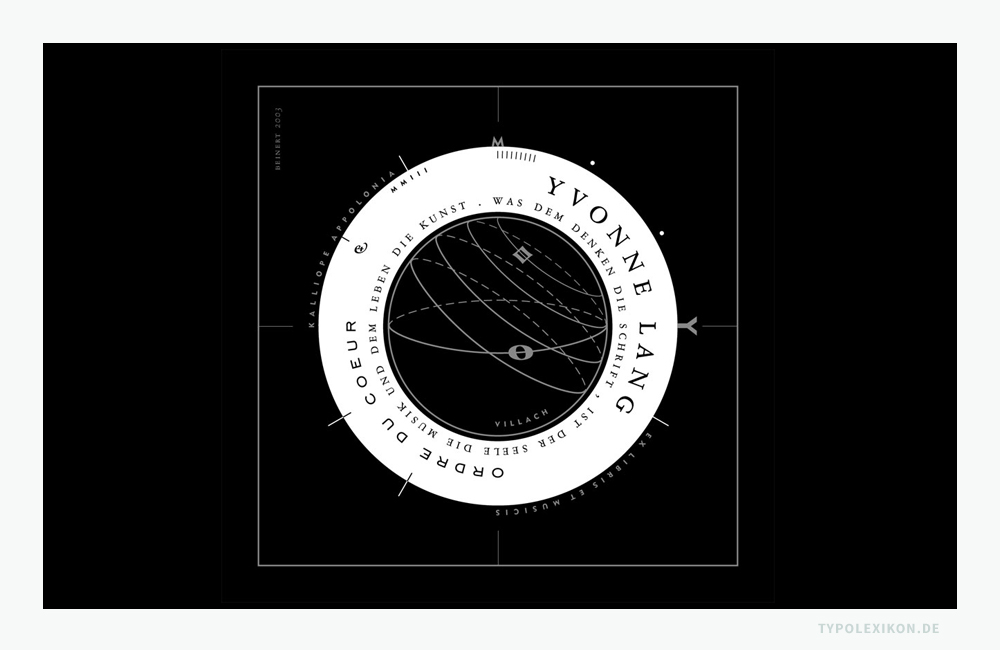
Exlibris
Buchbesitzzeichen; Bücher- oder Bibliothekszeichen; typografisches oder/und grafisches Bucheignerzeichen oder -geberzeichen. In ein Buch geklebtes, drucktechnisch vervielfältigtes, kleinformatiges (Papier-)Blättchen, das auf den Besitzer des Buches hinweisen soll. Alternative Schreibweise »Ex Libris«.
Da Buchbesitzzeichen ursprünglich von Besitzern ganzer Bibliotheken verwendet wurden, bürgerte sich auf ihnen die Inschrift »Ex libris« vor dem Namen des Eigentümers ein, weshalb sie auch kurz »Exlibris« genannt wurden. 1)  Hypostasierung des Substantivs »Exlibris« (Pluralitantum) von lat. »ex libris« für »aus den Büchern« bzw. übertragen »aus der Bibliothek« oder »aus der Bücherei«. 2)
Das Exlibris entwickelte sich in Deutschland in der ersten Hälfte des 15. Jahrhunderts mit dem Wiege- bzw. Inkunabeldruck aus der Tradition kalligraphischer und illuminierter Besitzervermerke, Deckelpressungen (z.B. Supralibros) und Gravuren auf den Metallschließen des Bucheinbandes. 3) Experten gehen davon aus, dass die ältesten Exlibris (z.B. Igler-Exlibris, Buxheimer Exlibris) zwischen 1470 und 1491 im Holzschnitt entstanden sind. Exlibris wurden anfänglich vom Adel, der Geistlichkeit und von reichen Patriziern bei Offizinen in Auftrag gegeben. Neben seiner ursprünglichen Verwendung als Eigner- oder Geberzeichen wird das Exlibris heute insbesondere als Sammlerobjekt verwendet. Ein Exlibris wird traditionell auf den inneren Vordeckel (linker vorderer Vorsatz) eines Buches eingeklebt. 4)
Exlibris der Münchner Hofbibliothek aus dem Jahre 1618. Quelle: Bayerische Staatsbibliothek, München.
Typografisches Exlibris einer Musikwissenschaftlerin und Germanistin aus dem Jahre 2003. Dieses quadratische Buchbesitzeichen enthält vielerlei Andeutungen, die sich auf den Lebensweg der Eignerin beziehen. Grafikdesign: © Wolfgang Beinert, Berlin.
Typografisches Exlibris einer Musikwissenschaftlerin und Germanistin aus dem Jahre 2003. Dieses quadratische Buchbesitzeichen enthält vielerlei Andeutungen, die sich auf den Lebensweg der Eignerin beziehen. Grafikdesign: © Wolfgang Beinert, Berlin. Weiterführende Informationen online verfügbar unter https://www.wolfgang-beinert.de/portfolio/grafikdesign-webdesign-yvonne-lang-austria/.
Im Exlibris vereinen sich buchwissenschaftliche, gestalterische und soziologische Aspekte. Ein schlichtes typografisches Exlibris (Schriftexlibris) besteht aus dem auf einem Blatt gedruckten Hinweis »Ex libris« sowie dem Namen des Eigentümers oder des Schenkers bzw. Stifters (z.B.: »Ex libris Wolfgang Beinert« für »Aus der Bibliothek von Wolfgang Beinert«). Alternative Formulierungen können u.a. »Dieses Buch gehört …« oder »Signum bibliohecac …« sein. Darüber hinaus kann ein grafisches Exlibris Worte, Wahl- oder Sinnsprüche, Illustrationen, Fotos, Monogramme, Wappen, Emblemata, Symbole, Signete etc. enthalten, die auf die Vorlieben, den sozialen Status oder die Biographie des Besitzers hinweisen. Oft beinhaltet die Gestaltung eines Exlibris auch versteckte Anspielungen, Codes oder verschlüsselte Botschaften, die sich dem Betrachter auf Anhieb nicht erschließen.
Exlibris werden infolge der Exlibriskunst und des Sammelns in unterschiedliche Kategorien und charakteristische Gruppen eingeteilt, beispielsweise in
• Bucheignerexlibris (Eigentümer des Buches)
• Donatorenexlibris (Stifterexlibris, Buchgeberexlibris)
• Doppelexlibris (z.B. Wappen- und Inschriftblättchen oder zwei Eignerexlibris zweier Besitzer einer Bibliothek, z.B. Eheleute)
• Eigenexlibris (das Exlibris eines Designers bzw. bildenden Künstlers, das er für sich selbst gestaltet hat)
• Einklebeexlibris
• Gebrauchsexlibris (Exlibris, das nicht auf das Sammeln ausgerichtet ist)
• Luxusexlibris (Exlibris, das bereits bei der Gestaltung auf einen hohen Sammlerwert ausgelegt ist)
• Stempelexlibris (Buchstempel)
• Supralibros (geprägtes Super-Exlibris)
• Universalexlibris (loses Blatt oder bereits im Buchdeckel eingedruckt, so das der jeweilige Besitzer seinen Namen selbst eintragen kann)
• Ornament-, Schrift- und Textexlibris. 5)
Exlibris werden in der Regel von Typografen/innen, Grafikdesignern/innen (siehe Grafikdesign), Illustratoren/innen oder bildenden Künstlern/innen gestaltet und in unterschiedlichen Drucktechniken, z.B. in Hochdruckverfahren, Tiefdruckverfahren oder photomechanischen Verfahren [6] hergestellt. Bedruckt werden mehrheitlich industriell hergestellte oder handgemachte grafische Papiere 6)  in unterschiedlichen Sorten. Gebrauchsexlibris erreichen selten Formate über dem traditionellen Oktavformat, welches etwas kleiner als ein Taschenbuch ist. Luxusexlibris sowie Eigenexlibris können auch größere, unzweckmäßige Formate aufweisen.
Im Sinne der Kunstgeschichte gelten das 16. Jahrhundert und die Epoche des Jugendstils (Jahrhundertwende, etwa 1896–1910) als die Blütezeiten der Exlibriskunst. Zu den prominenten Gestaltern von Exilbris zählen beispielsweise Albrecht Dürer (1471–1528), Hans Holbein der Jüngere (1497/98–1543), Lucas Cranach der Ältere (1472–1553), 7)  Giambattista Bodoni (1740–1813), Wilhelm Busch (1832–1908), Pablo Picasso (1881–1973) oder Jan Tschichold (1902–1974). Große öffentliche Exlibrissammlungen besitzen u.a. das British Museum in London, die Bayerische Staatsbibliothek in München, die Österreichische Nationalbibliothek in Wien, das Gutenberg-Museum in Mainz und das Germanische Nationalmuseum in Nürnberg (siehe Museen Typografie und Schrift). Die Zahl der Privatsammlungen ist unbestimmbar. Zahlreiche Sammler haben sich weltweit in sogenannten Exlibrisgesellschaften und -vereinen organisiert. In Deutschland wurde 1891 der erste Verein dieser Art von Friedrich Warnecke (1837–1894), einem deutschen Heraldiker und Kunsthistoriker, unter dem Namen »Ex-libris-Verein zu Berlin« gegründet. 8)  9)  10)  11)
↑1 Quelle: Meyers Konversations-Lexikon (5. Auflage) von 1897, Verlag des Bibliographischen Instituts, Leipzig und Wien.
↑2 Quelle: Kluge, Etymologisches Wörterbuch der deutschen Sprache, 24. Auflage, Walter de Gruyter, Berlin/New York.
↑3 Quelle: Gustav A. Seyler, Kanzleirath, Bibliothekar und Lektor im Ministerium für Handel und Gewerbe: Illustriertes Handbuch der EX-LIBRIS-KUNDE, Verlag von J. A. Stargardt, Berlin 1895.
↑4 Anmerkung: Exlibris werden vereinzelt auch auf den Hinterdeckel des Buches geklebt.